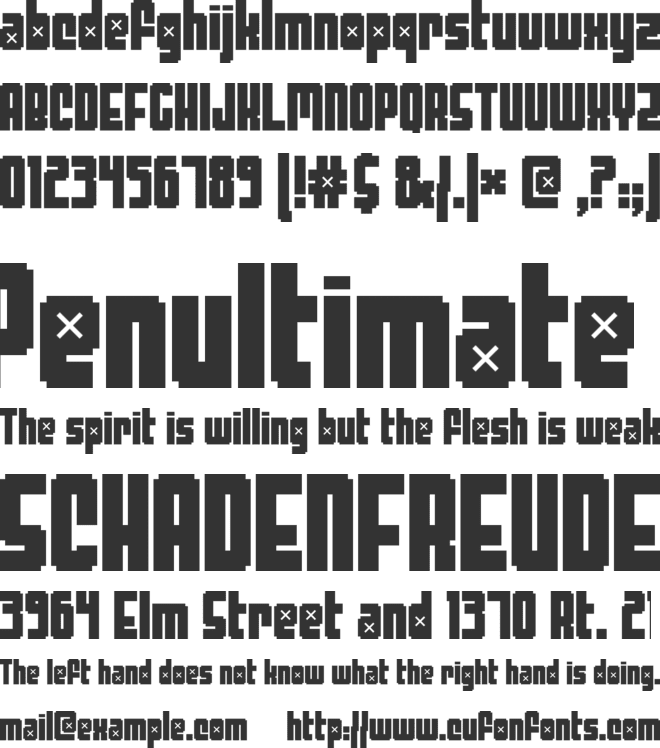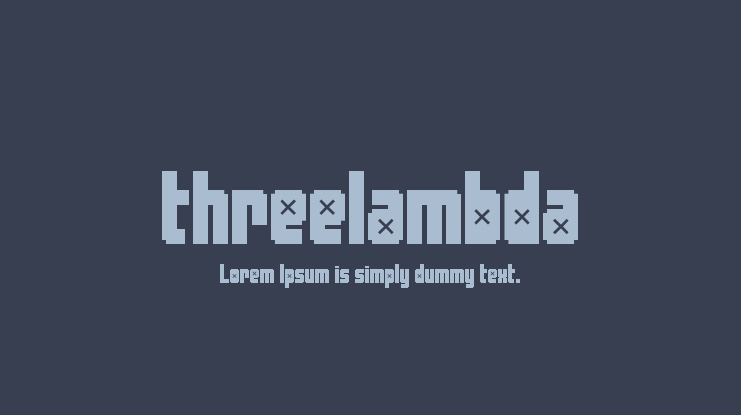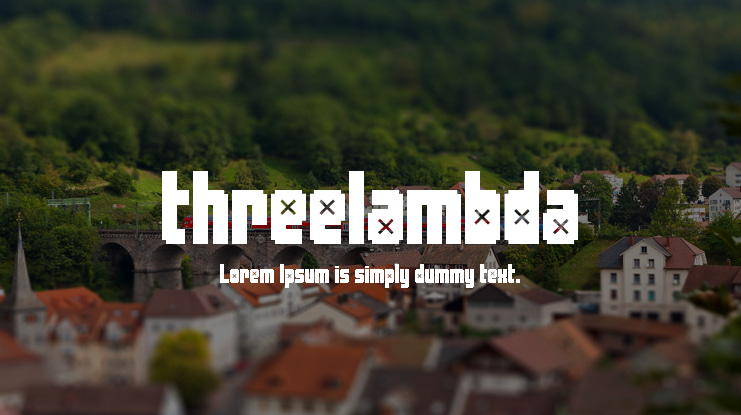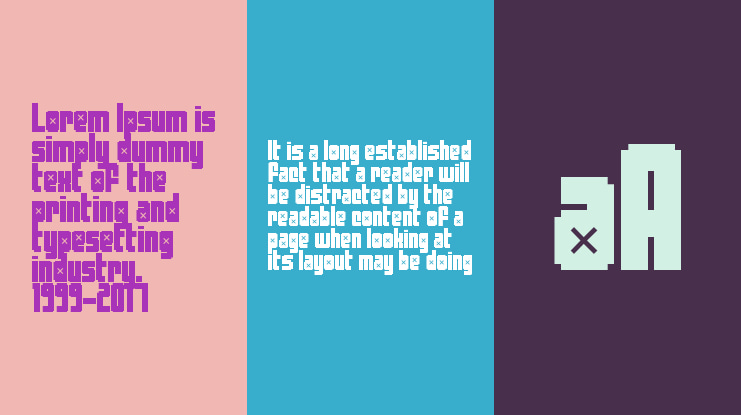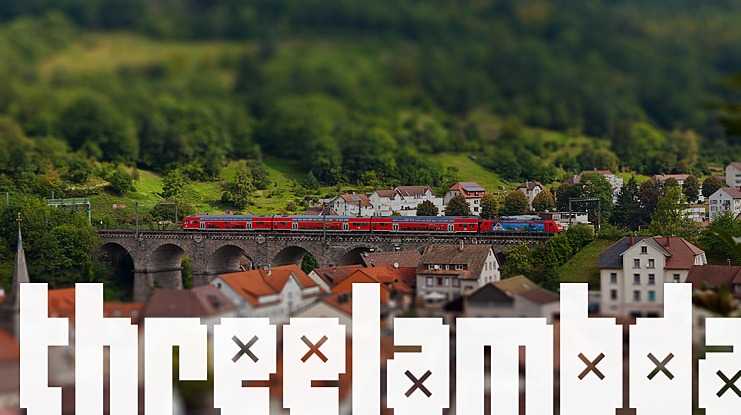
threelambda Font
Diseño experimental de familia tipográfica desarrollada para Nolup (argentina) por el grupo IXS. Libre para cualquier tipo de uso, salvo proyectos estrictamente comerciales. www.facebook.com/ideasxs www.facebook.com/nolup.laboratorio www.behance.net/piterosporum